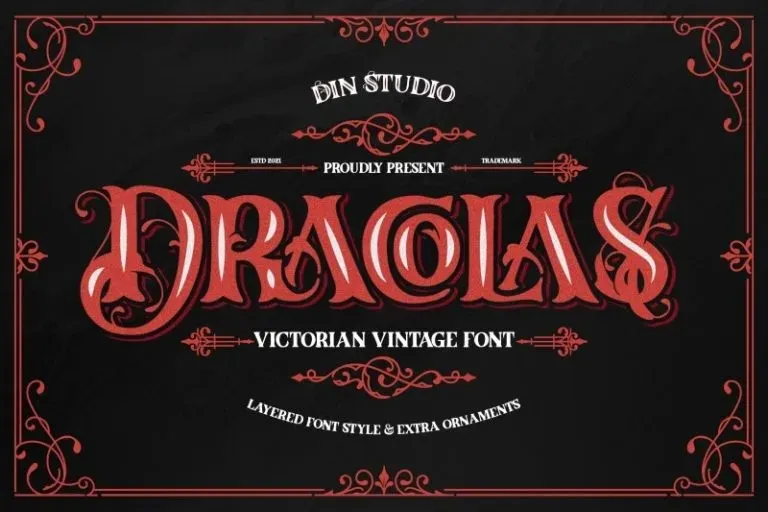
A fonte Dracolas é um tipo de letra blackletter clássico que parece vintage e elegante. Ela foi projetada com bordas afiadas e tem aparência moderna, tornando-a ideal para uso em diferentes projetos como logotipos, capas de livros, cartazes, camisetas de marketing e anúncios. Além disso, oferece recursos úteis como ligação de caracteres que a tornam perfeitamente adaptada à demanda de criação de materiais multilíngues. Esta fonte artística é particularmente interessante para muitos projetos, pois combina elegância com simplicidade e modernidade. É uma excelente opção para quem procura um pacote completo de soluções gráficas que pode ser aplicado em várias aplicações, desde a criação de logotipos até ao design dos mais variados materiais de marketing. A Dracolas é perfeita para quem busca um estilo único e moderno na sua identidade visual.